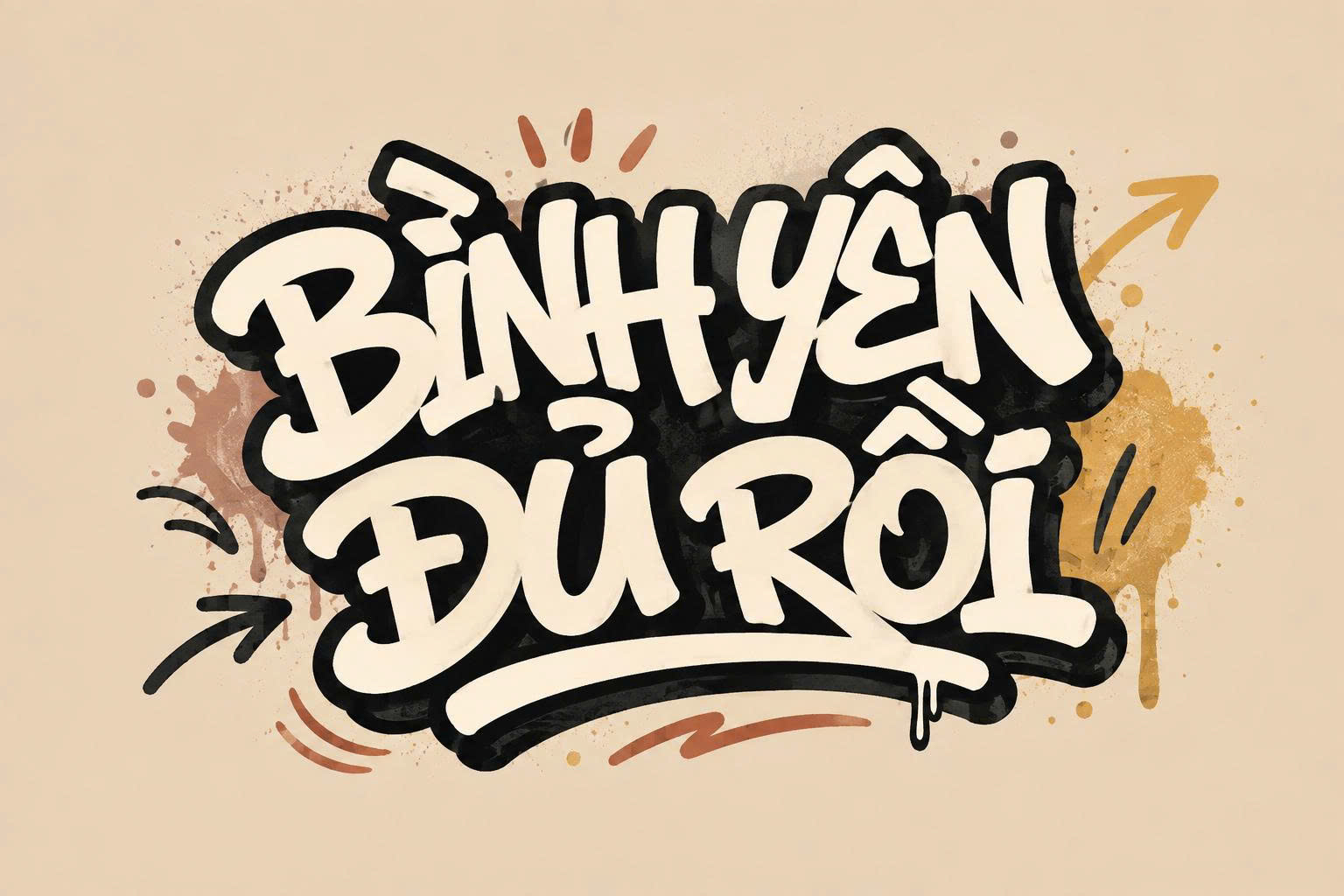
Đặc điểm thẩm mỹ của các dòng font Graffiti Việt hóa
Khác với các dòng font chữ truyền thống gò bó, Graffiti mang lại một không gian sáng tạo không giới hạn với những đặc trưng thị giác cực mạnh.
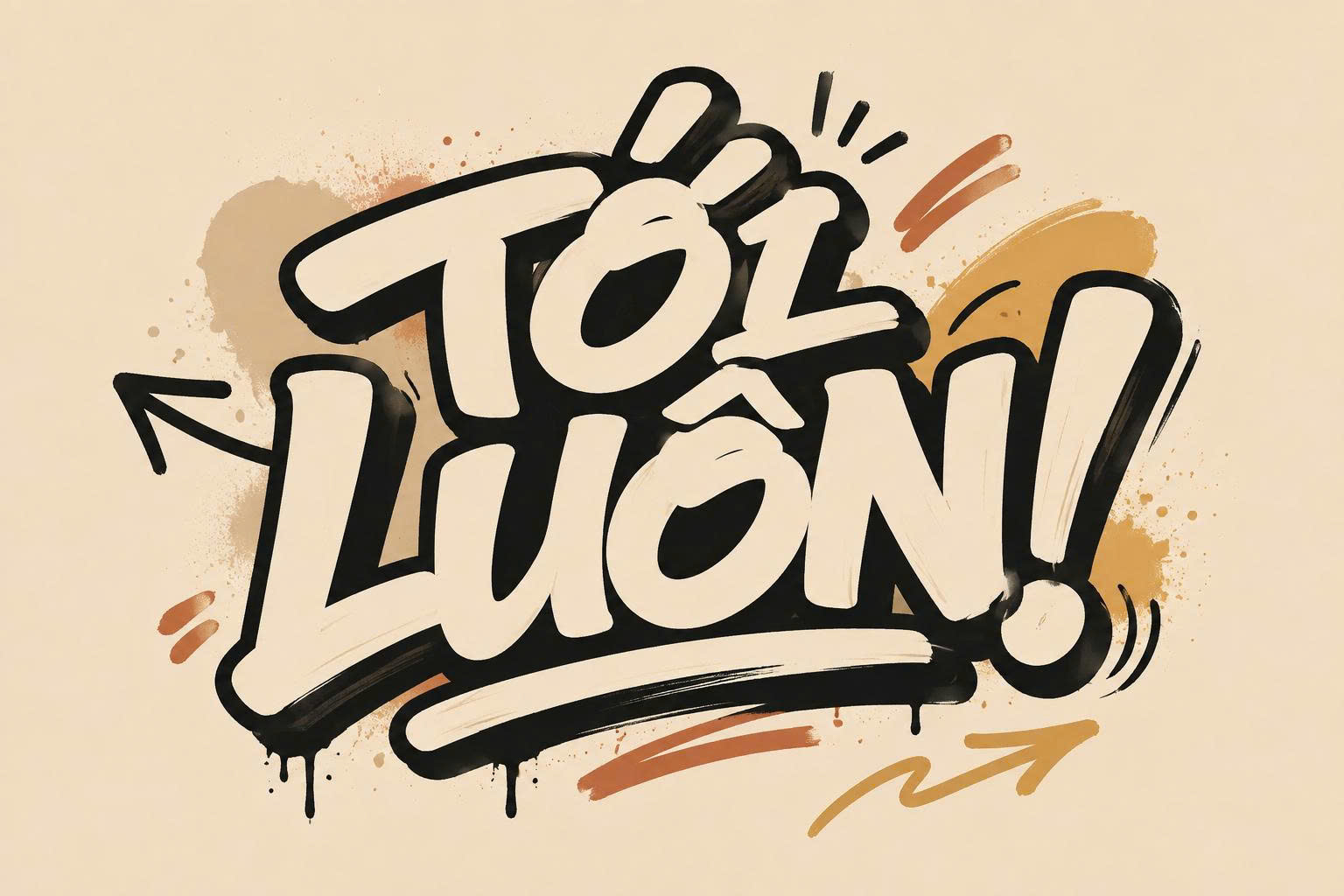
Phong cách tự do, phóng khoáng và tràn đầy năng lượng
Đặc trưng lớn nhất của font Graffiti Việt hóa là sự ngẫu hứng trong từng nét vẽ. Các ký tự thường được thiết kế với độ dày lớn, các đường cong chồng lấp hoặc những nét hất mạnh mẽ tạo cảm giác chuyển động không ngừng. Phong cách này giúp bản thiết kế của bạn toát lên sự cá tính, bụi bặm và vô cùng hiện đại, dễ dàng thu hút sự chú ý của phân khúc khách hàng Gen Z.
Cấu trúc chữ đa dạng: Từ Bubble đến Wildstyle
Hệ sinh thái font Graffiti rất phong phú, từ những bộ chữ dạng bong bóng (Bubble) mập mạp, dễ thương đến các dòng Wildstyle phức tạp với nhiều chi tiết cắt xẻ táo bạo. Tại Doozypack.vn, chúng tôi đã tuyển chọn và Việt hóa những bộ font dễ ứng dụng nhất, đảm bảo các dấu thanh như “sắc, huyền, hỏi, ngã, nặng” được đặt cân đối, không làm mất đi nhịp điệu Typography đặc trưng của nghệ thuật đường phố.